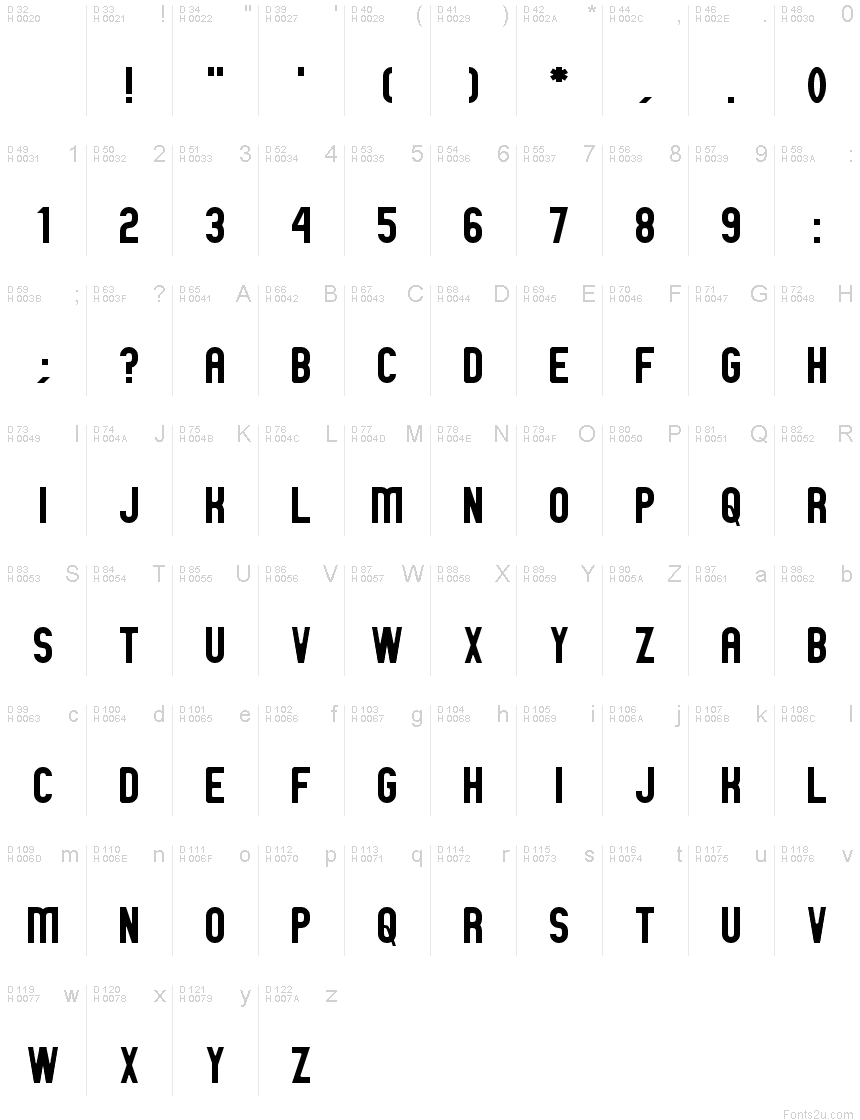
GM Exp od G.M. to darmowy, skondensowany krój bezszeryfowy o wyrazistym, industrialnym charakterze. Wysokie, ciasno upakowane litery tworzą solidną bryłę, a kwadratowe krzywizny i proste cięcia nadają mu surowy, techniczny wygląd. Dzięki wąskiej szerokości możesz zmieścić mocne nagłówki w ograniczonej przestrzeni bez utraty siły przebicia, co sprawia, że każde słowo brzmi śmiało i zdecydowanie.
Wykorzystaj GM Exp, aby nadać odzieży miejskiej, plakatom, oznaczeniom, grafikom sportowym, okładkom albumów czy opakowaniom technologicznym jednolity i zdecydowany styl. Ten darmowy font najlepiej sprawdza się w dużych rozmiarach, gdzie jego zwarte formy pozostają czytelne nawet z odległości. Połącz go z prostym, geometrycznym krojem bezszeryfowym o mniejszej grubości w tekście głównym, aby przekaz pozostał silny, a jednocześnie czytelny.
GM Exp Norm